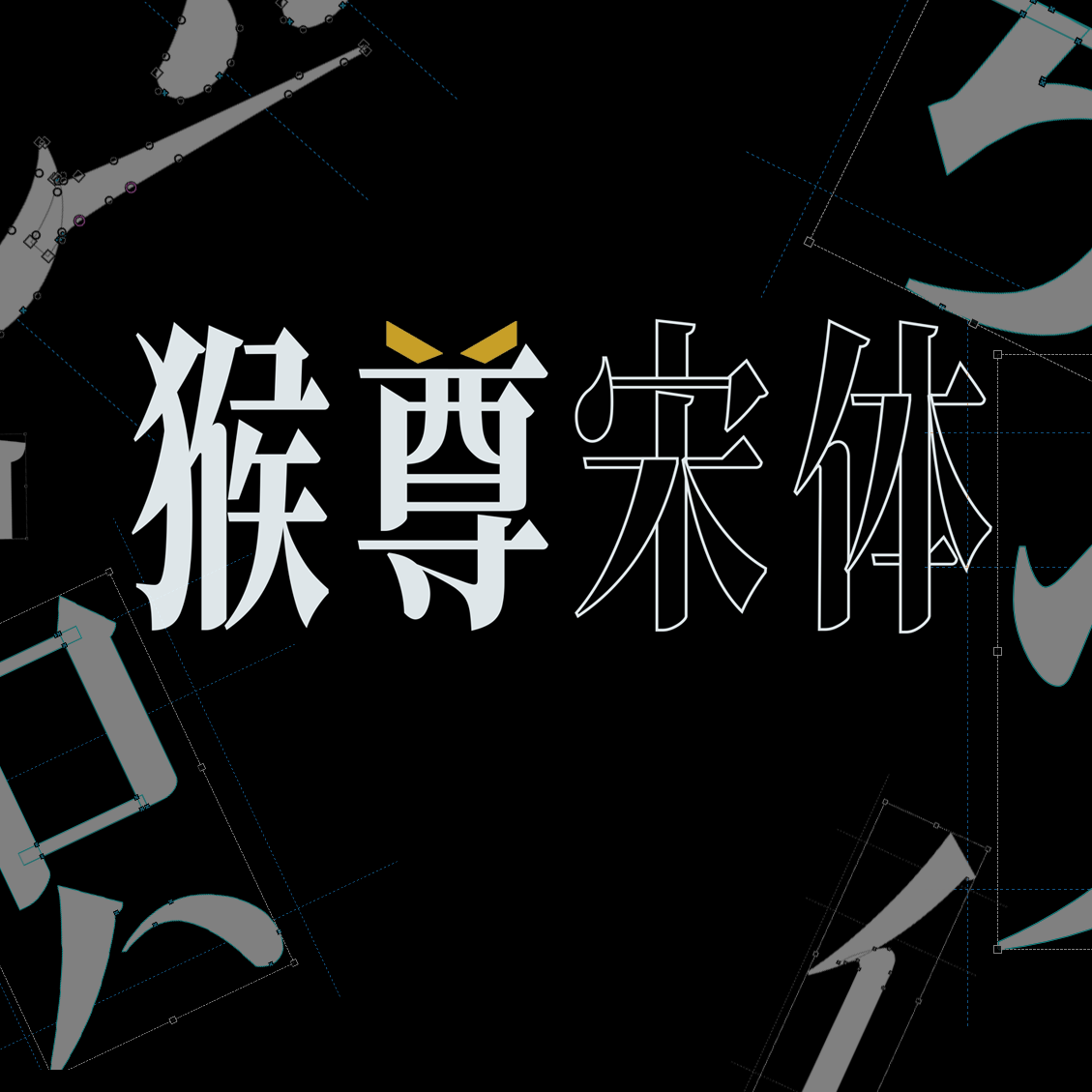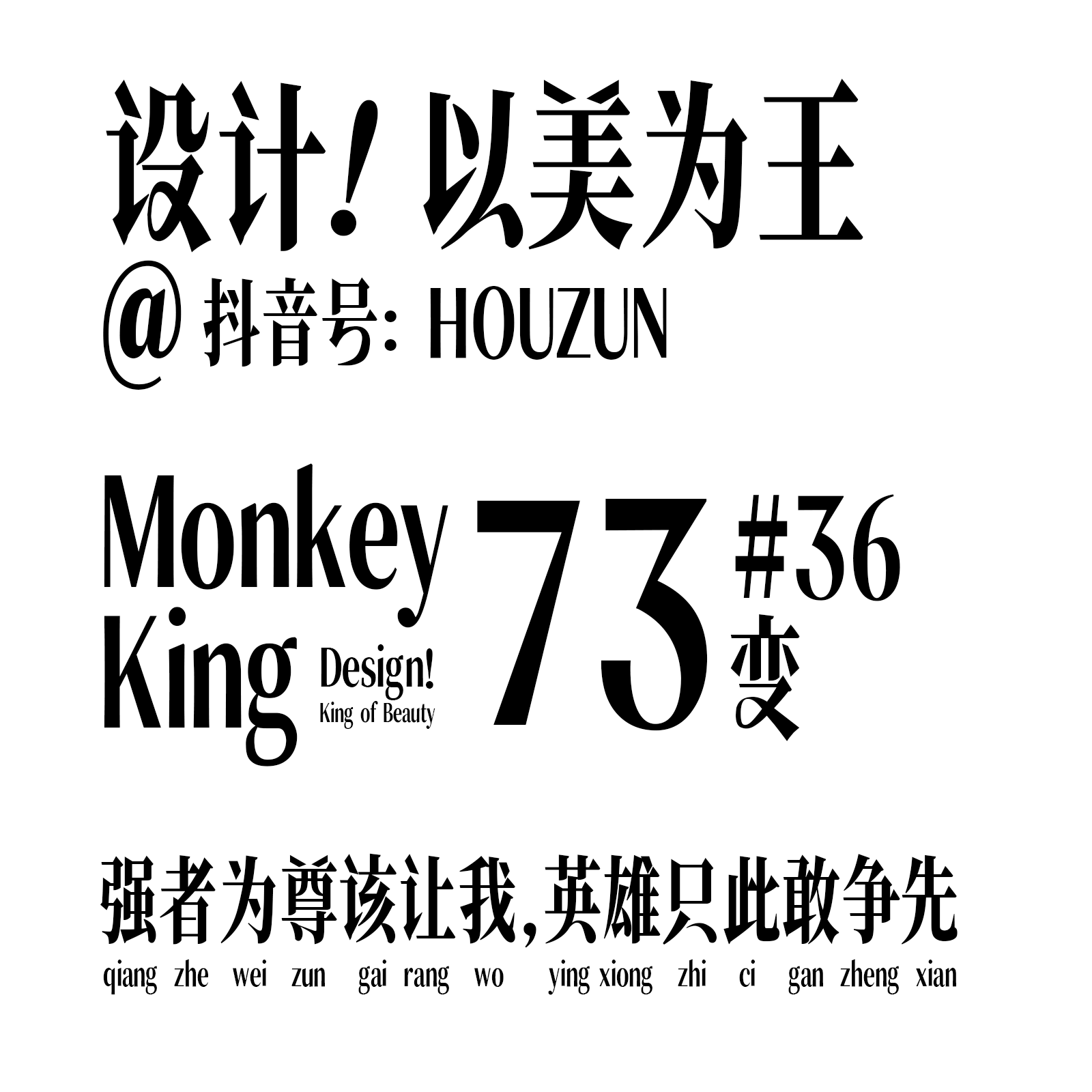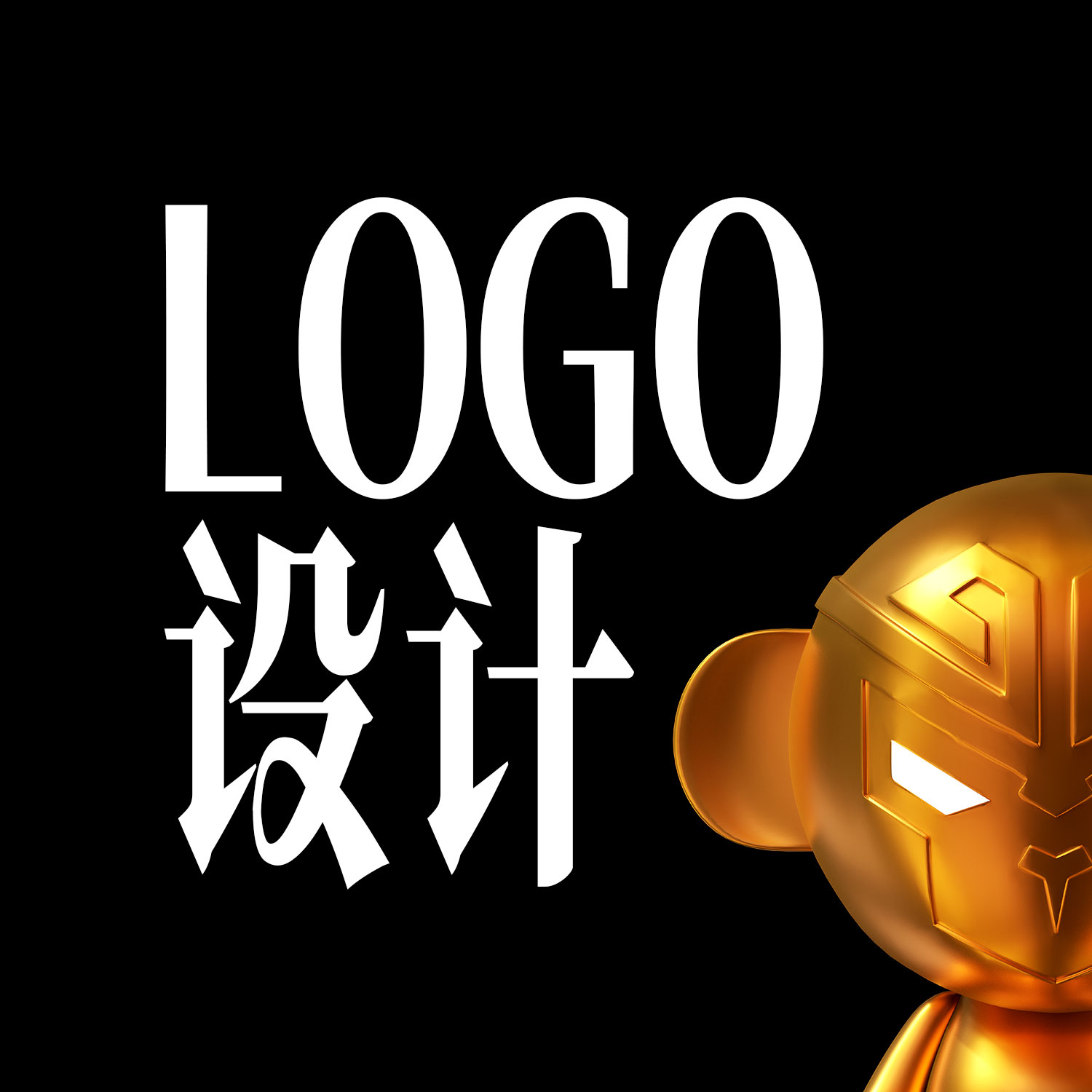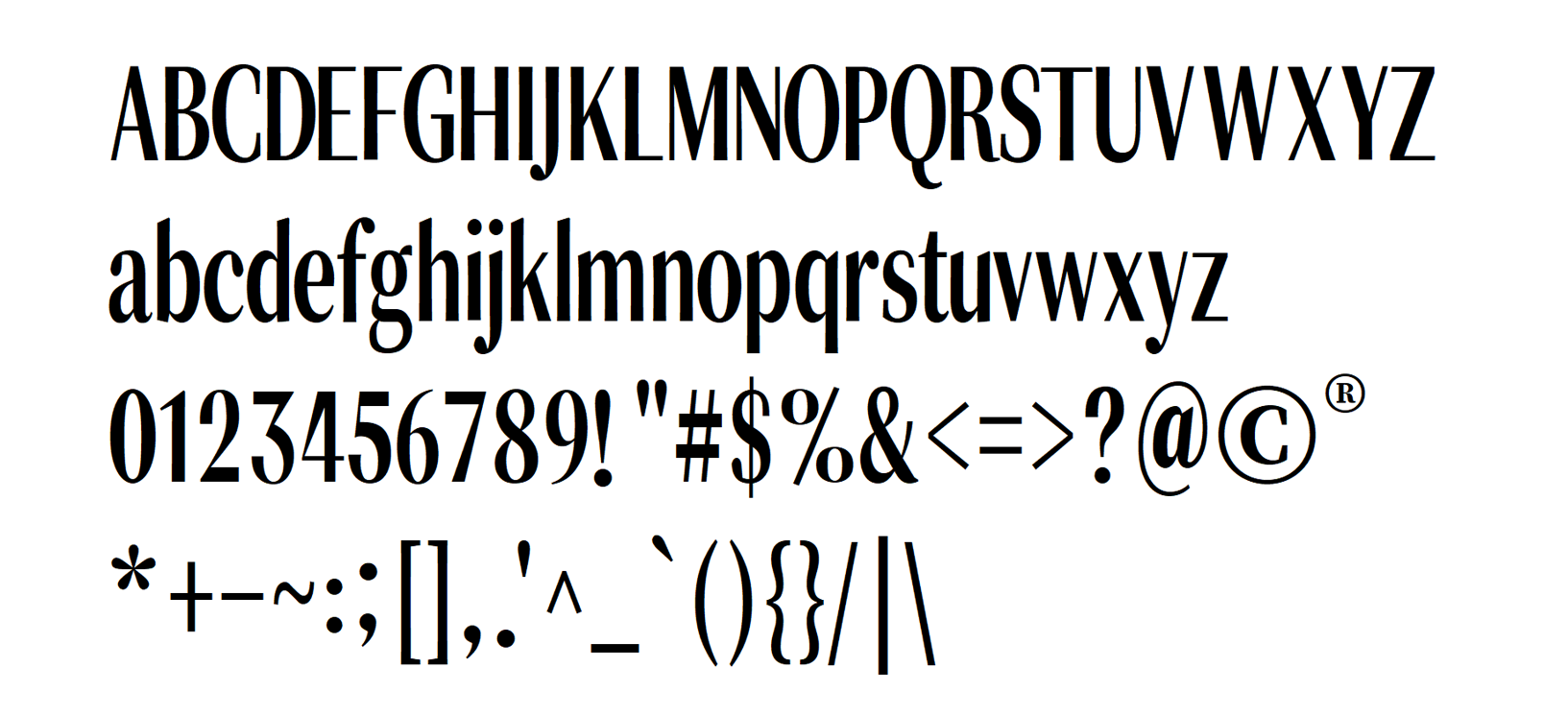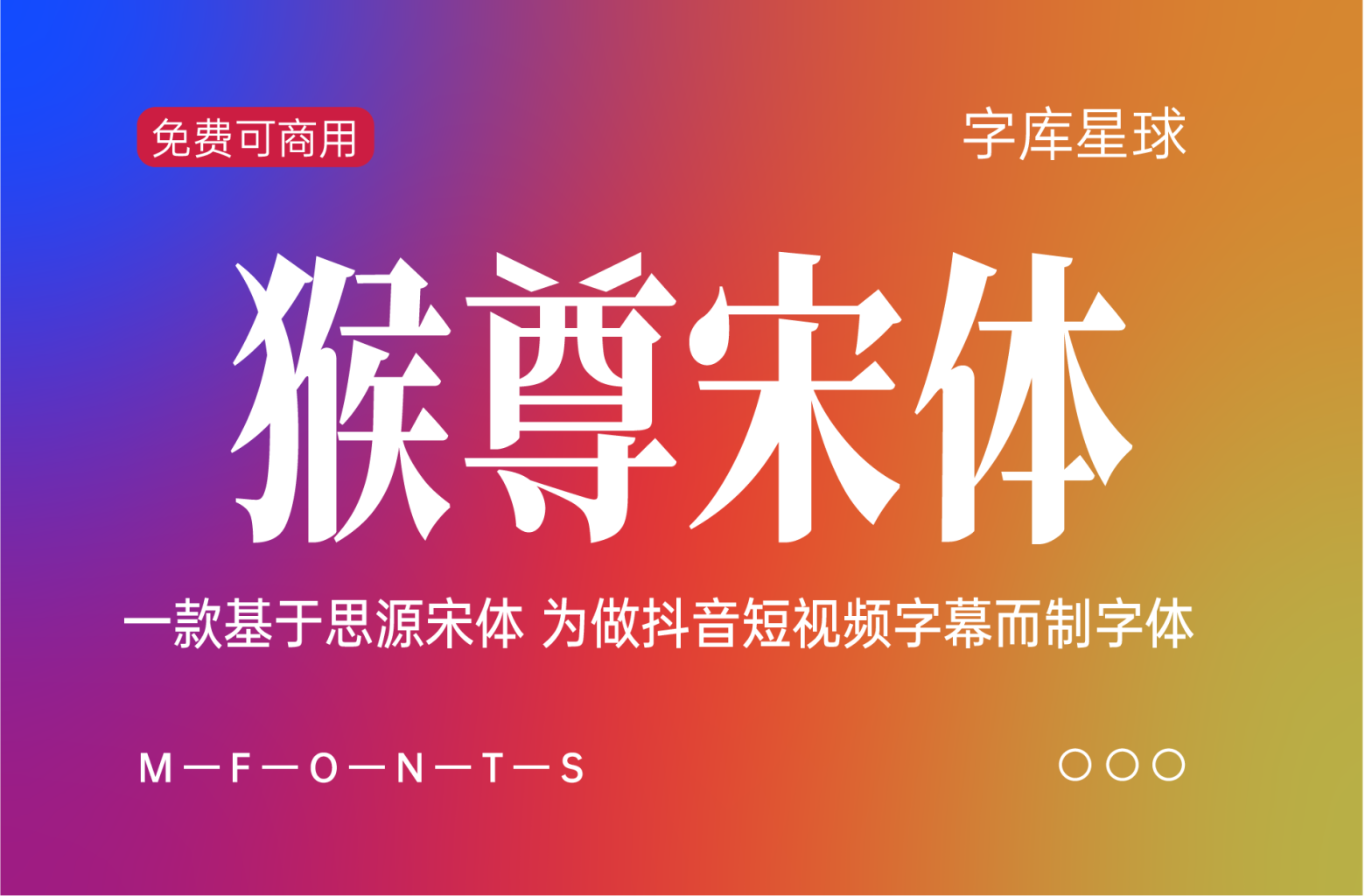
猴尊宋体是由抖音设计博主猴尊提供的一款免费商用字体,基于思源字体的比例更改为黄金比例值,部分字体笔画、字母、数字、符号等字体重构设计,为短视频的手机竖屏阅读时,一行文字可放下更多(更大)的字,用于大标题时,依具精致感。字体保留原笔画不合并(转曲线后可见,你可随意继续创新),个别笔画加入书法手写的笔画感觉,字体有种独特高雅的高级感!
文章标题:猴尊宋体